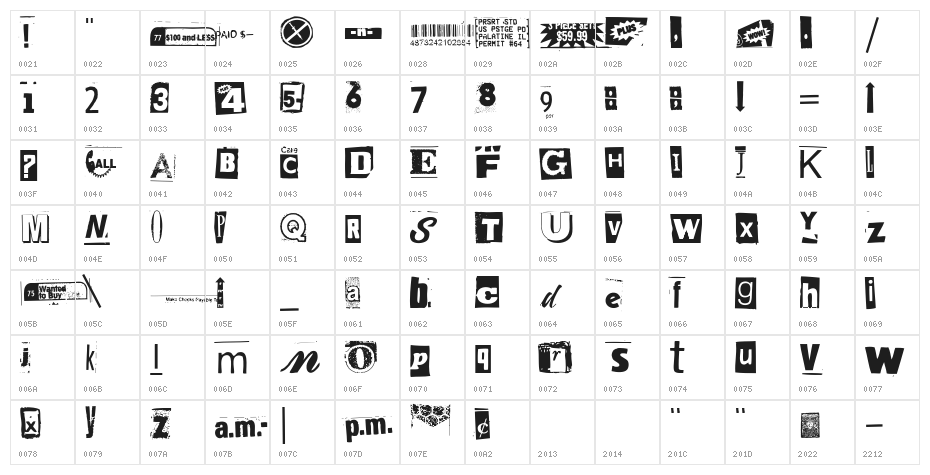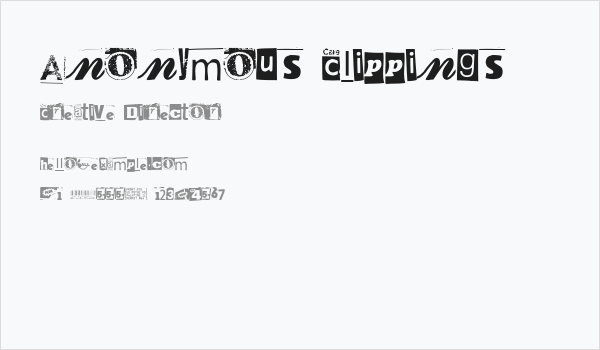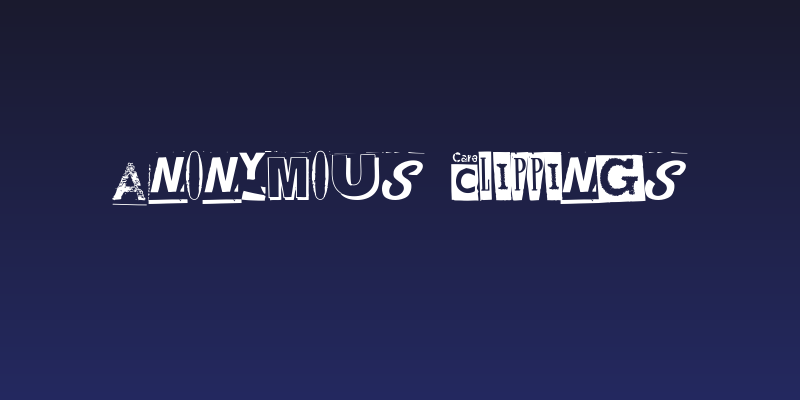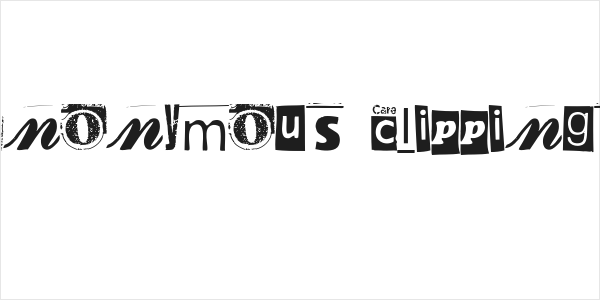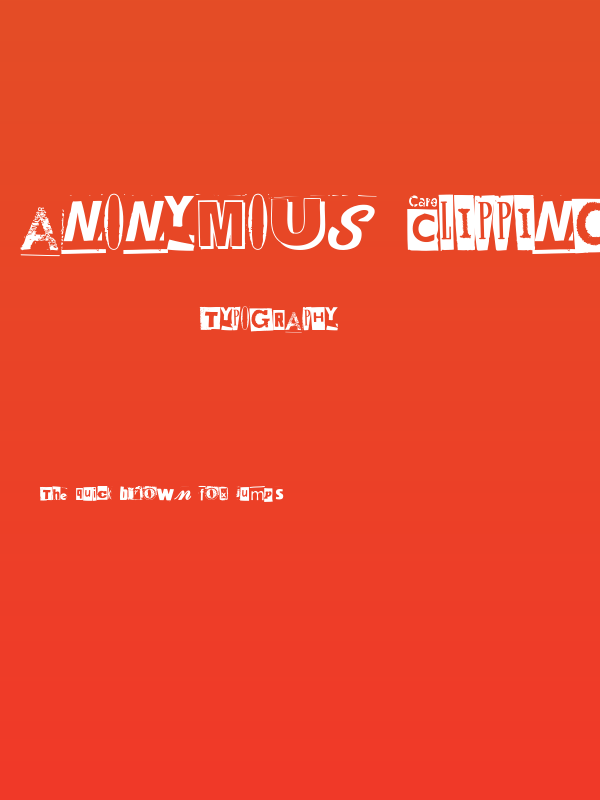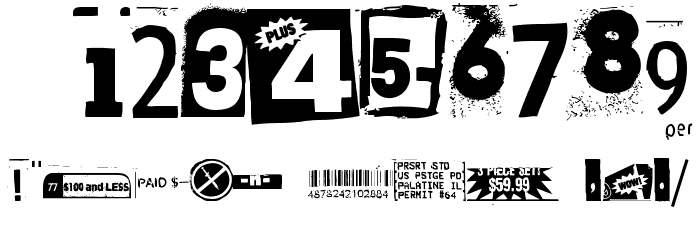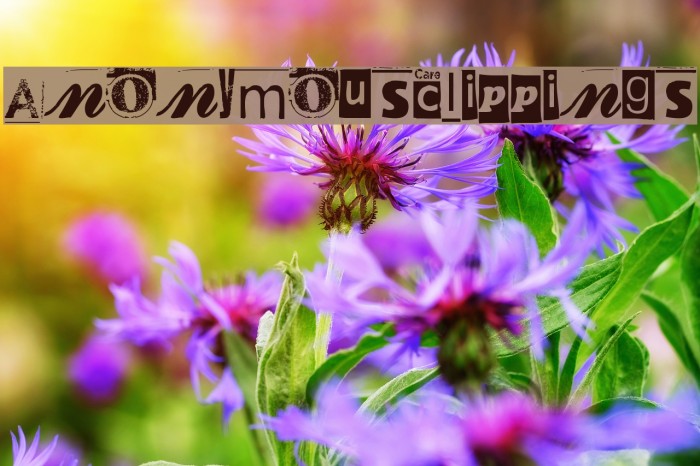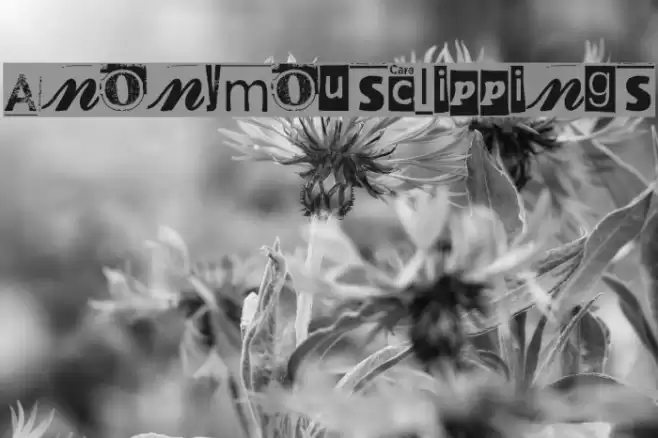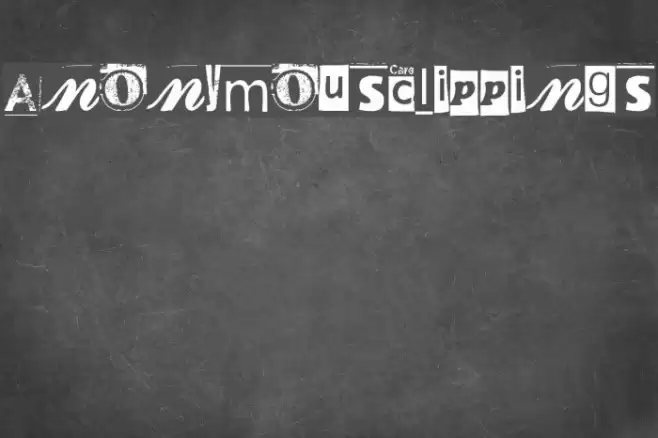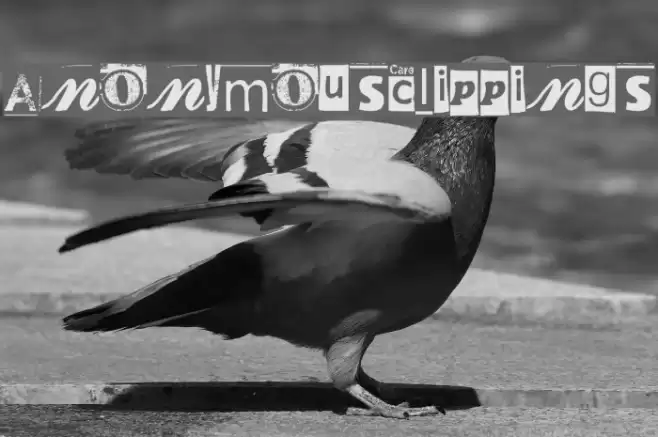
Anonymous Clippings Font
| Общий стиль | Vintage, Grungy, Eclectic |
| Область применения | Logos, Posters, Album Covers |
| Рекомендуемые проекты | Ideal for use in mystery-themed posters, edgy graphic designs, album covers, or any project needing a unique, eclectic look. |